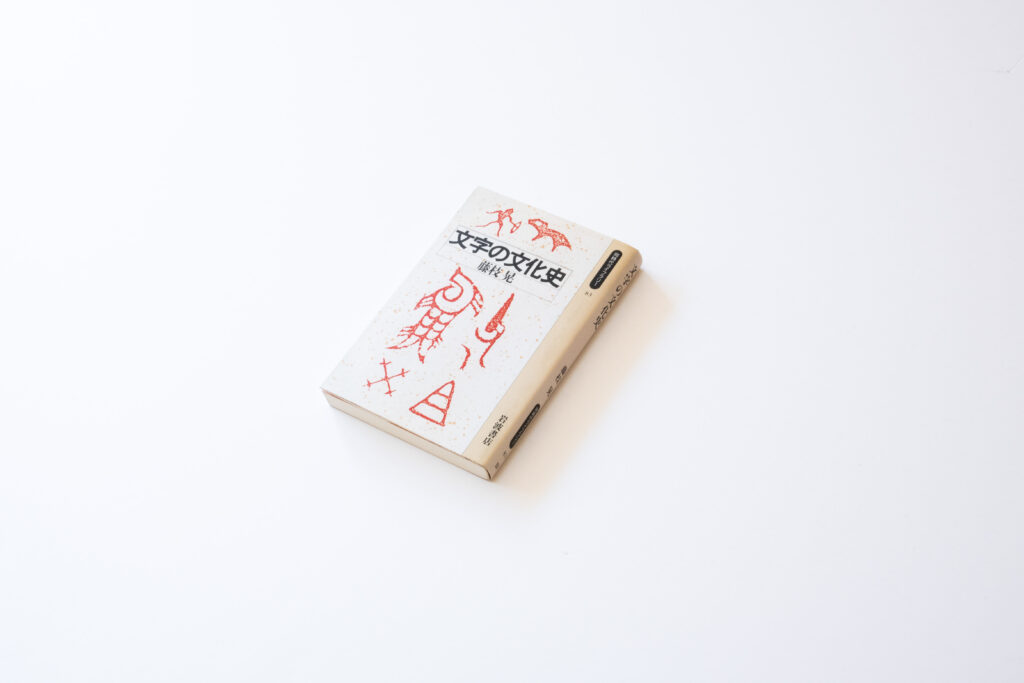
TPの書庫から『文字の文化史』
今回は、藤枝晃著の『文字の文化史』を紹介します。
本書には象形文字から始まり漢字の誕生、印刷に至るまでの歴史や書体の変遷が書かれています。写経など貴重な図版も豊富です。 皇帝の文字、臣下の文字など現在までに生まれた書体がどのような立場の人のためのもので、その限られた人のものから万人のものになるまでの経緯は興味深かったです。
文字の造形や筆法にのみ焦点を当てたものではなく、筆などの道具、文字が記される素材、本などの形式の変遷についても書かれていて、文字が生まれて読まれたその背景も横断的に知りたい方におすすめです。
続いて『文字の文化史』に関連して弊社の鈴木から選書へのコメントです。
『図説 中国書道史』は図版の選択と分量が適切で、手元に置いておくガイドブックとして好適。書体の変遷を図解したフローチャートは、長大で複雑な漢字書体史の理解を助けてくれる。
『文字の文化史』
著者:藤枝晃
『季刊墨スペシャル第9号 図説中国書道史 書を学ぶ人のための』